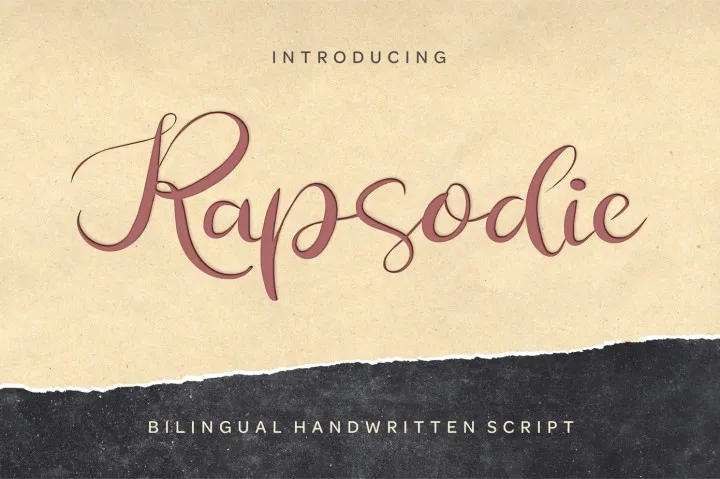
Rapsodie Script Font
Através das mãos do designer 0001themes, surge Rapsodie Script Font, uma elegante fonte de escrita com suporte bilingüe que combina letras inglesas e russas em um mesmo design único. Este script multilíngue é perfeito para quem busca uma fonte original para projetos variados. Rapsodie não apenas oferece 300 símbolos, incluindo letras inglesas e russo, números e pontuação, mas também possui suporte para múltiplas línguas. Além disso, Rapsodie vem com uma extensa lista de ligaturas avançadas e outros recursos que o tornam ainda mais versátil. Se você está à procura de um design interessante ou precisa criar logotipos, nomes de lojas ou rótulos para sua empresa, este é definitivamente o atalho perfeito. Rapsodie foi testado e compatível com qualquer software, garantindo que seja facilmente integrada em seus projetos. Adquirir esta fonte será uma escolha consciente que irá trazer um toque único ao seu design. Sempre lembrando, a escolha certa pode tornar a diferença entre um simples desenho e algo extraordinário.